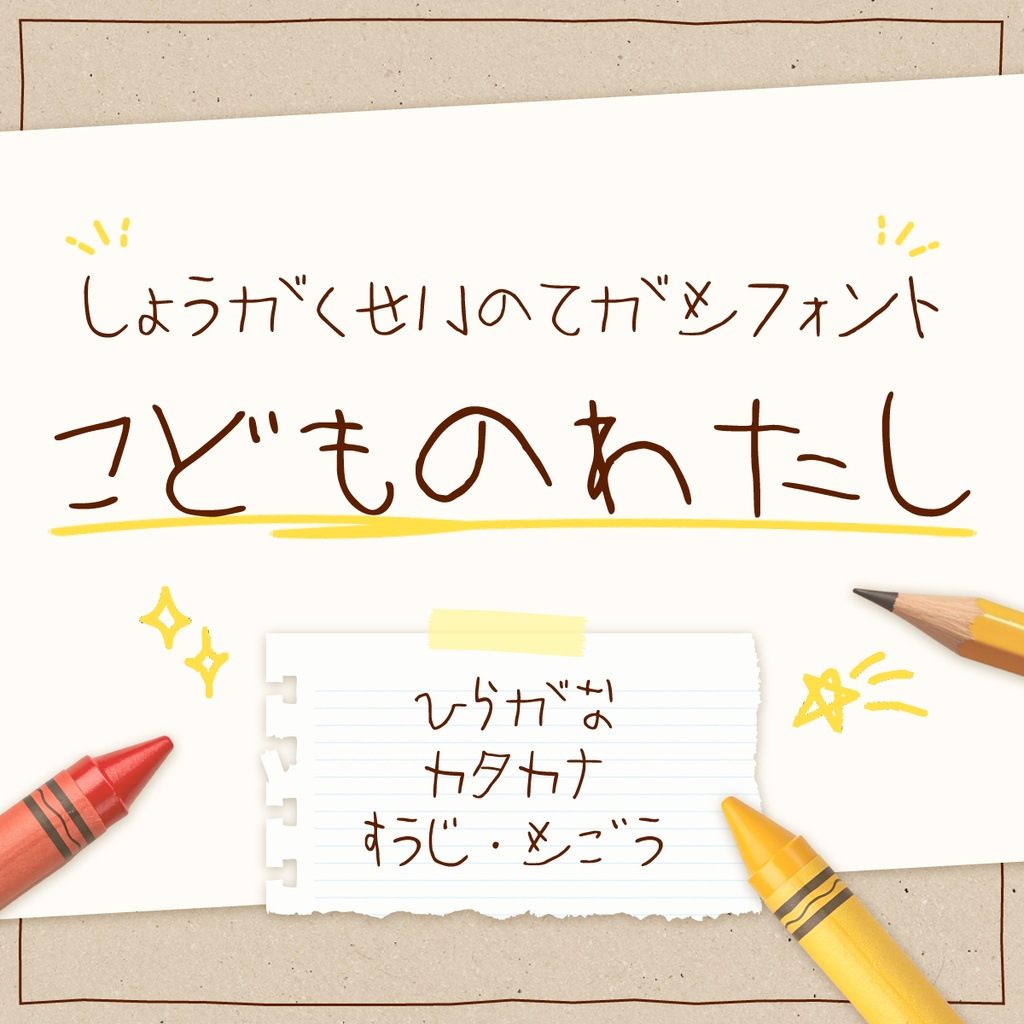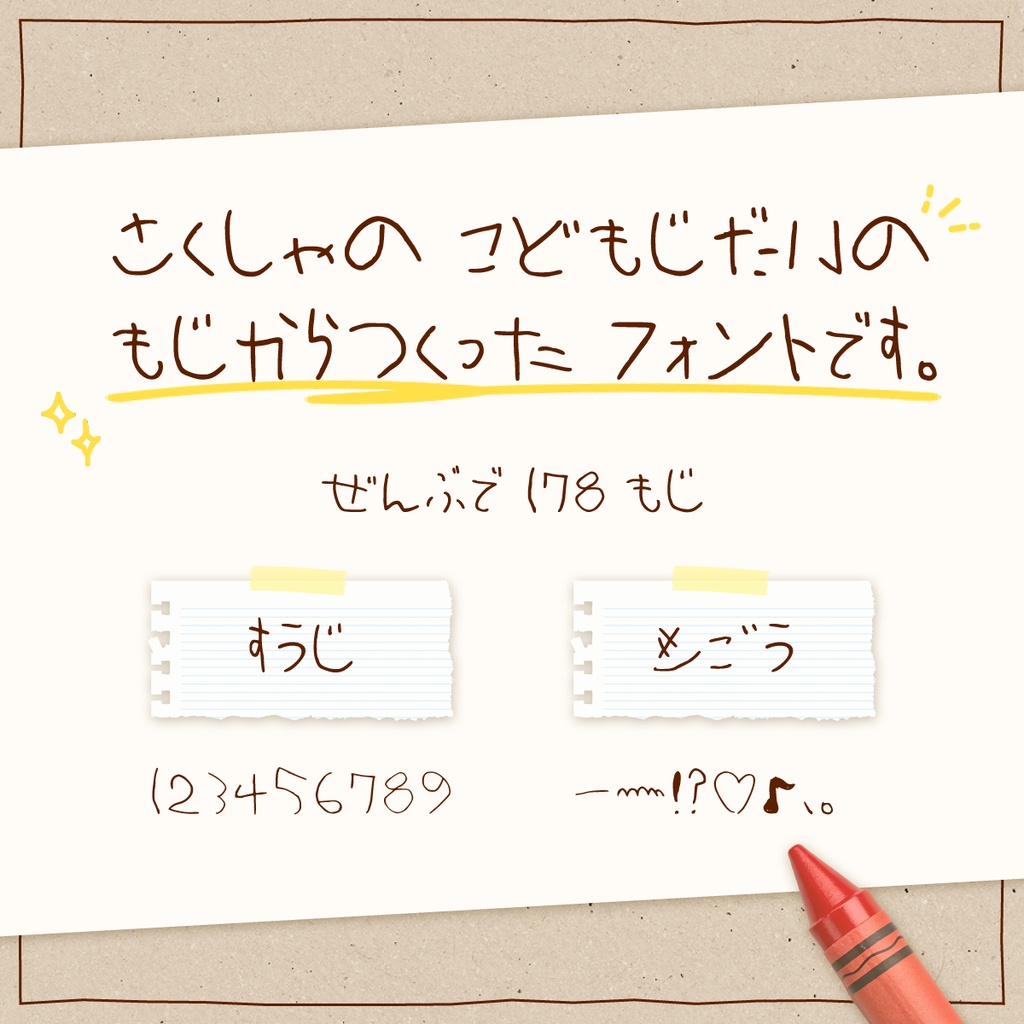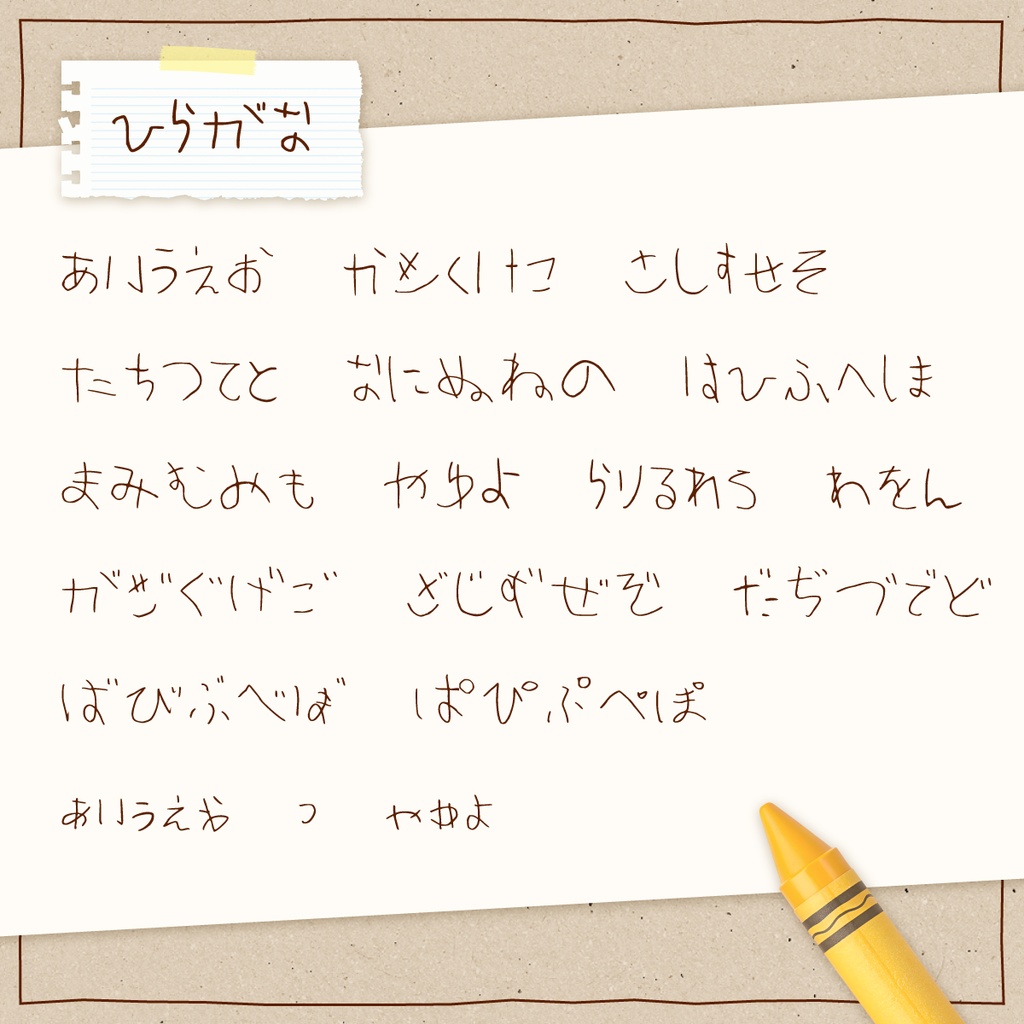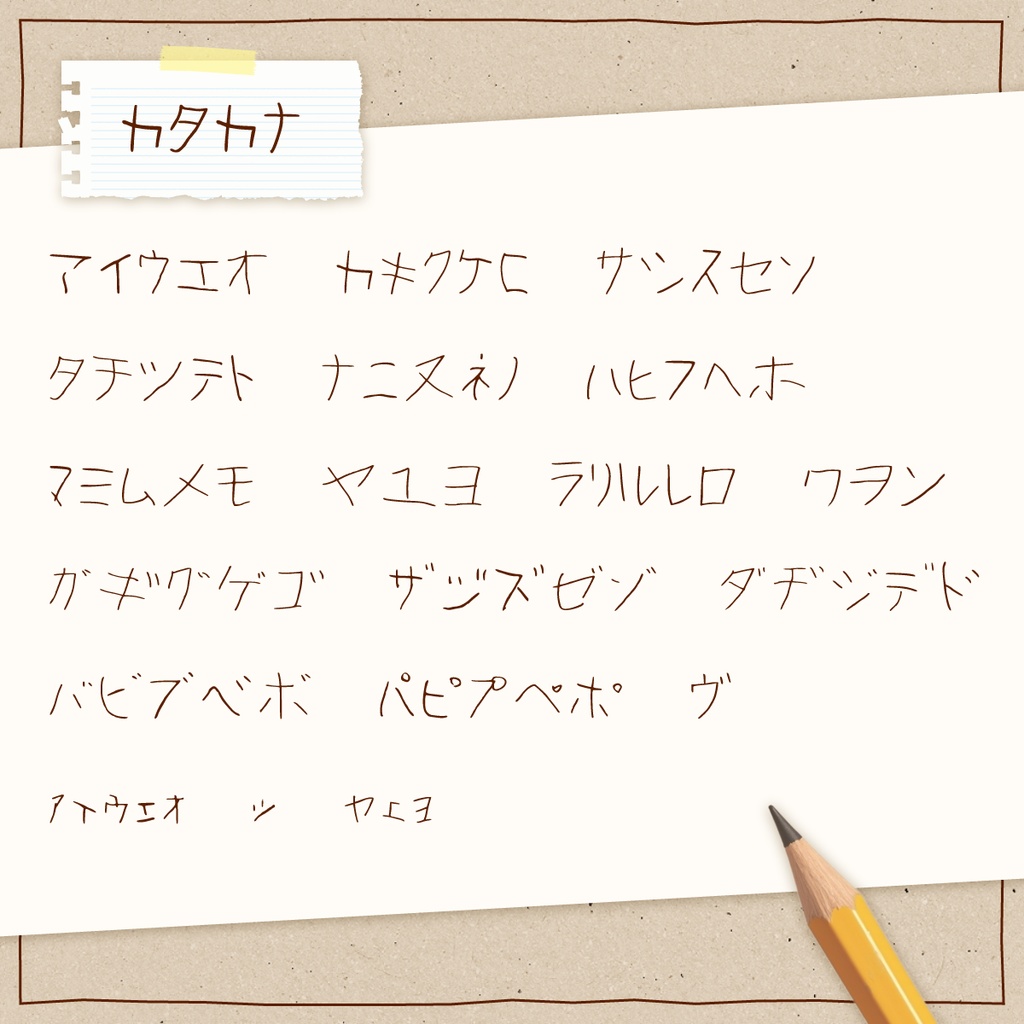
手書きフォント「こどものわたし」【商用利用可】
白紙ジャコウの子供時代の手書き文字(5〜6歳ごろ)をスキャンし、制作しました。 子供ならではの鏡文字がチャームポイントです。 収録文字:ひらがな・カタカナ・数字・一部記号(ー〜!?♡♪、。)計178字 【ファイル内容】 ・KodomoNoWatashi.otf ※CalligrahrおよびFontForgeを使用して作成しています。 【注意事項】 ・縦書きでは伸ばし棒(ー〜)が横向きで表示されます。伸ばし棒のみ90度回転させてご利用ください。 ・Office系ソフト、Adobe系ソフト、テキストエディットで動作確認済 ・本商品の著作権は白紙ジャコウに帰属します。 ・再配布禁止、自作発言禁止、改変禁止、商用利用可、クレジット不要 (使用報告していただけたら飛び上がって喜びます) 不具合があった際はBOOTHのメッセージ機能よりご連絡下さい。 このフォントのメイキング記事↓ https://note.com/hakushijaco/n/n178fa92f8c43